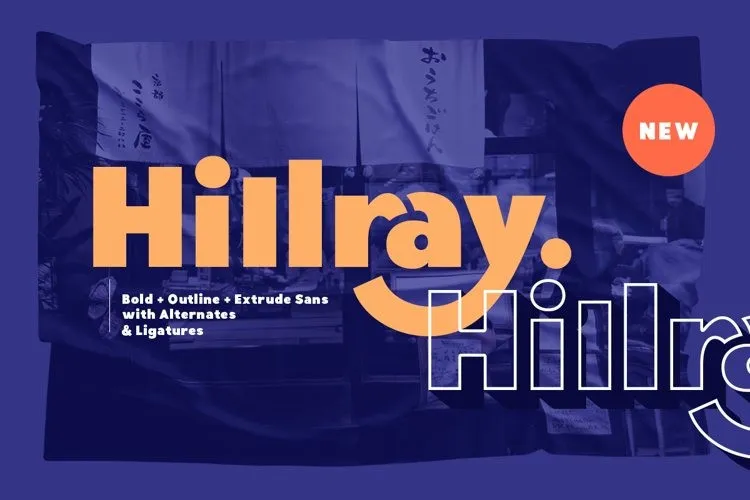
Esta é uma fonte sans serif autêntica e neat criada pelo designer Saridezra. Ideal para quem busca criar identidades únicas para sua marca ou arte urbana, essa fonte conta com estilos de destaque bold e que incorpora o estilo extrusado e contorno, complementando assim seu estilo mais convencional. Perfeita para aplicação em outdoors, branding, mercadorias e qualquer tipo de arte urbana! Além disso, suporta vários idiomas e já está codificada com PUA. Sempre uma opção versátil e atraente para quem procura personalidade em suas criações visuais. Descubra por que essa fonte é perfeita para qualquer projeto que você possa imaginar!